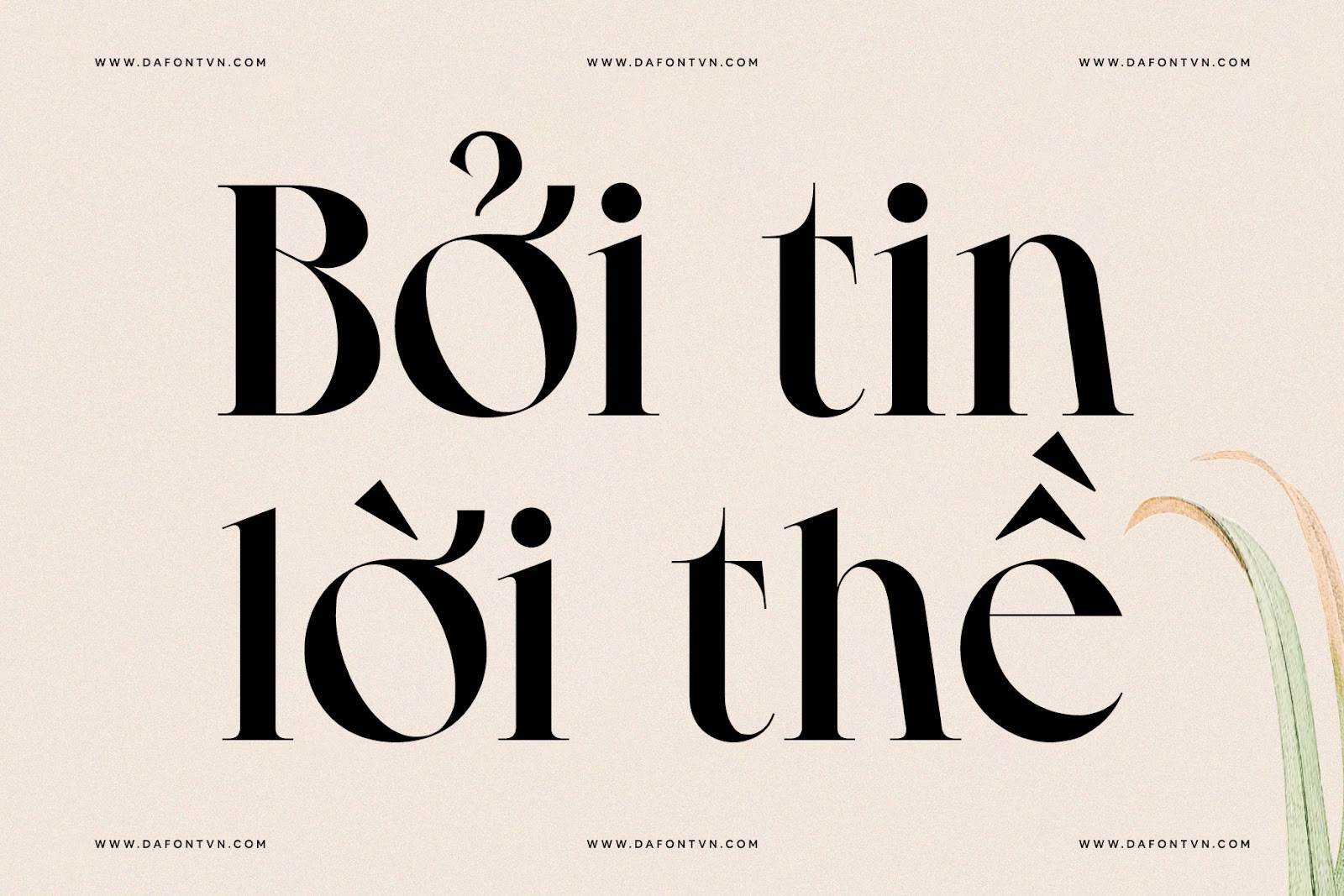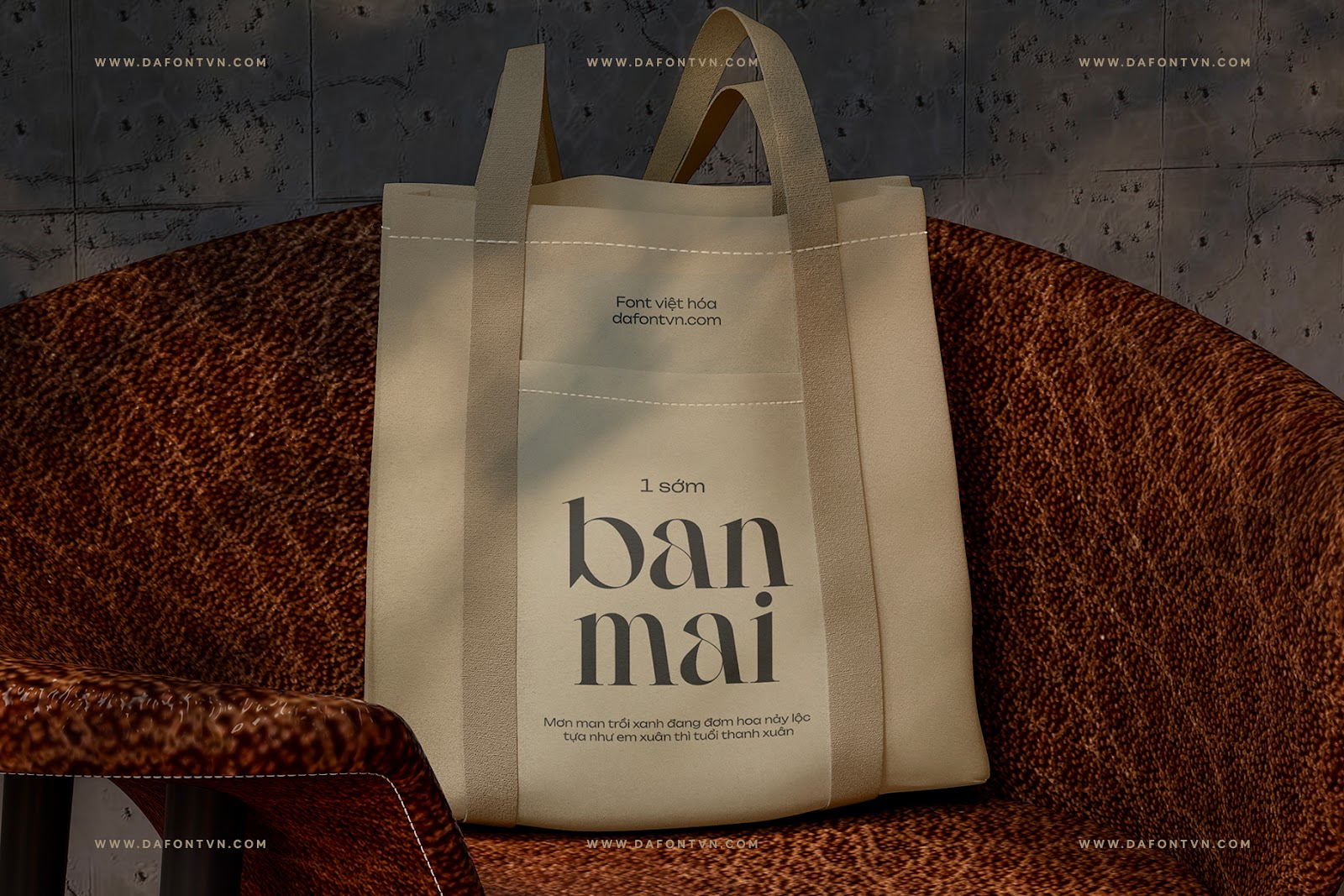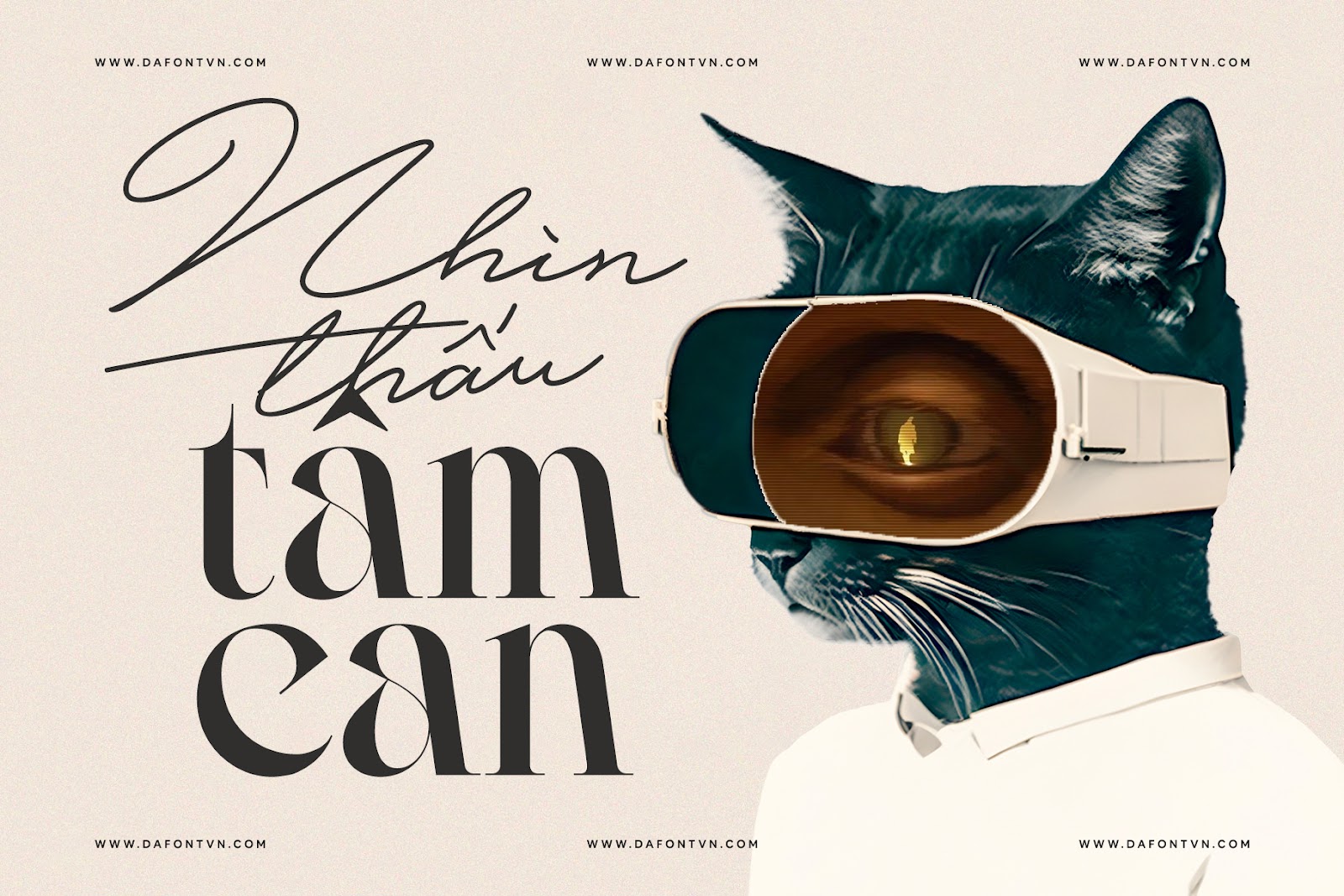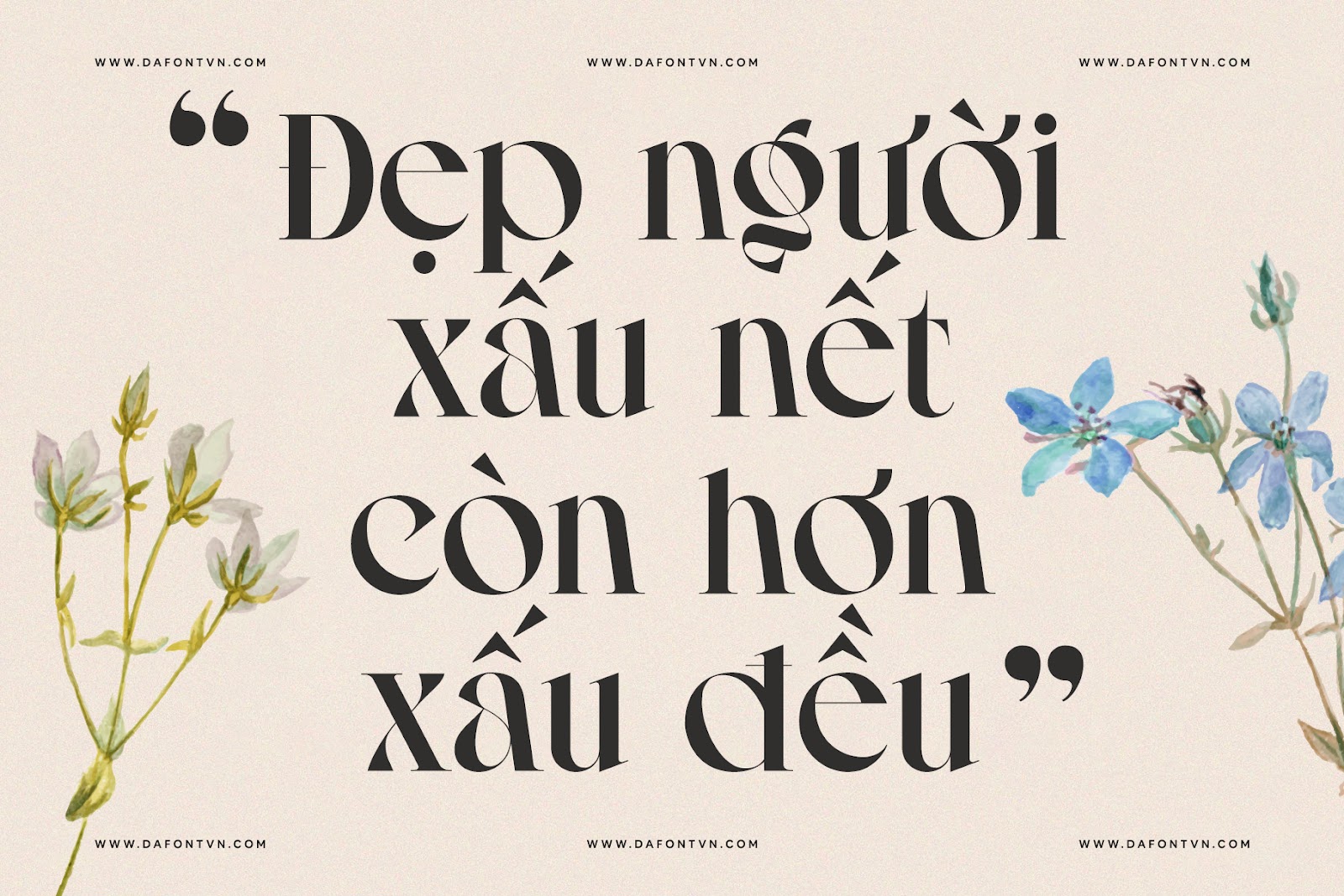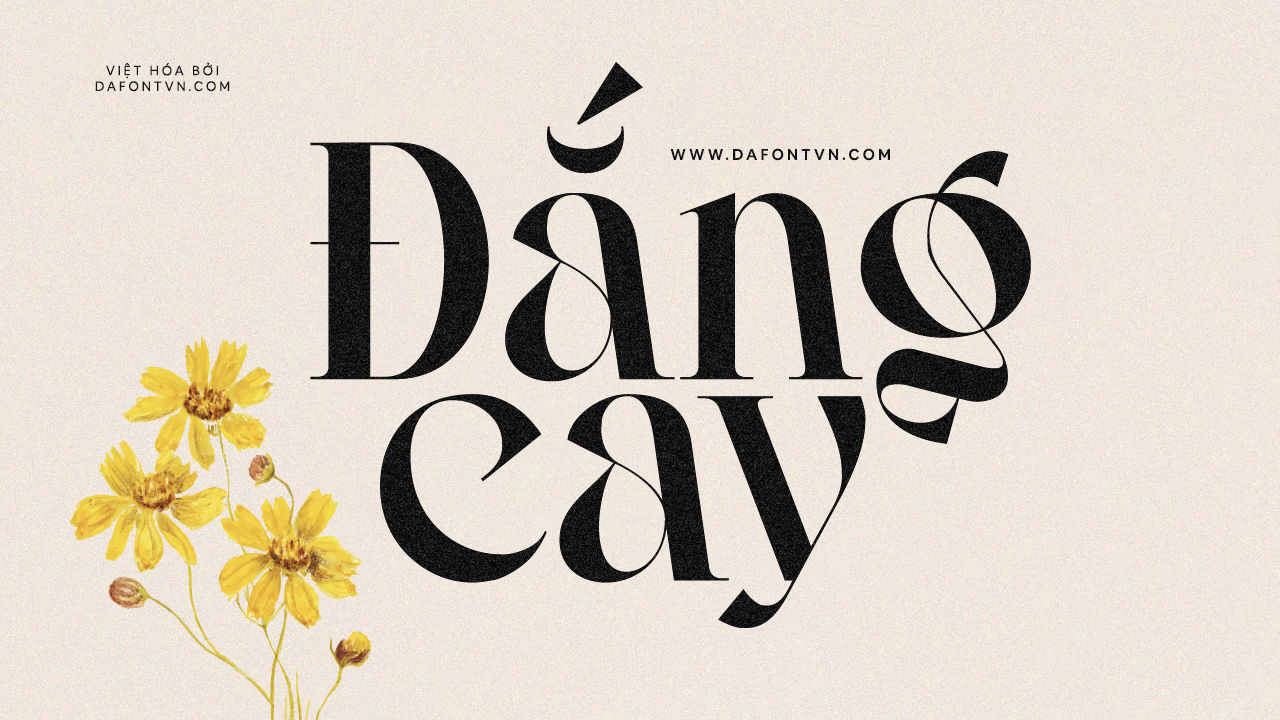
Avegra – là một phông chữ serif hiện đại đầy phong cách.
Các ký tự được thiết kế góc cạnh mang đến một vẻ ngoài ấn tượng, chứa các chữ hoa và chữ thường, tất cả dấu và con số. Avegra hoàn toàn hoàn hảo cho các dự án như thiết kế logo, xây dựng thương hiệu, bao bì sản phẩm, tiêu đề tạp chí…